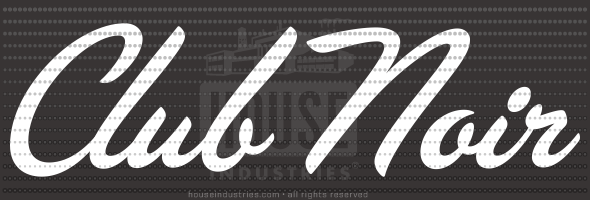
Hallo zusammen , Hilfe welche Schrift ist das
hallo , kann mir da jemand helfen, wär super dringend , um welche Schriften handelt es sich bei dem Logo ???
Die obere (»Club Noir«) sagt mir gar nichts, aber die untere Zeile (»Burlesque Club«) sieht für mich nach einer Zapf Chancery Medium Italic aus. Allerdings sind die Versalien etwas schwungvoller – kann Dir leider grad nicht sagen, obs zur Zapf Chancery evtl. alternative Versalien gibt oder ob da manuell nachgeholfen wurde. Aber da wird sich bestimmt noch jemand melden. :)
ok , super hoffe das mir noch jemand zur oberen Schrift was sagen kann da mir diese wichtiger ist !